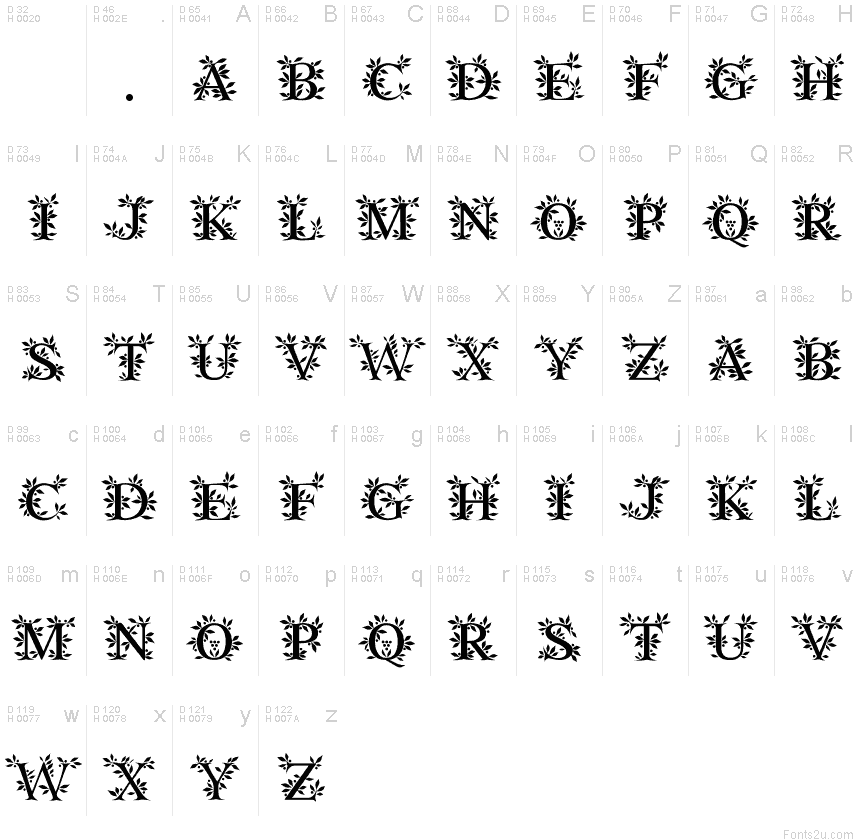
<p>Gayane StO od Studio Okno to darmowy, dekoracyjny krój typu display, którego litery wyglądają, jakby wyrosły z bujnego, zakorzenionego w tuszu pnącza. Każdy znak opiera się na solidnych szeryfowych formach, owiniętych gałązkami i liśćmi w kształcie kropli, co nadaje tekstowi namacalny, ręcznie rysowany, ogrodowy charakter. Rytm roślinności jest spójny w całym alfabecie, dzięki czemu nawet mocno zdobione tytuły pozostają czytelne i harmonijne.</p><p>Używając Gayane StO, nadasz botanicznego klimatu zaproszeniom ślubnym, etykietom produktów organicznych, logotypom marek eko, okładkom książek, plakatom wydarzeń i kartkom okolicznościowym. Ten darmowy font najlepiej sprawdza się w dużych rozmiarach, gdzie gęste liście mogą „odetchnąć”; zestaw go z czystym, geometrycznym bezszeryfowym krojem w tekście głównym, aby zachować świeżość i równowagę projektu.</p>
Gayane StO